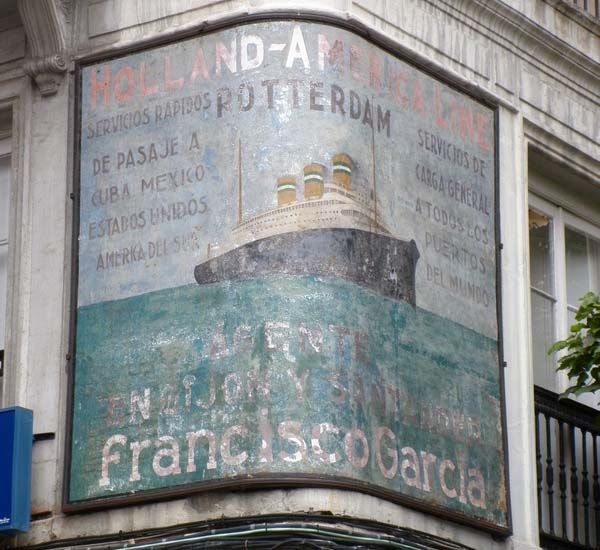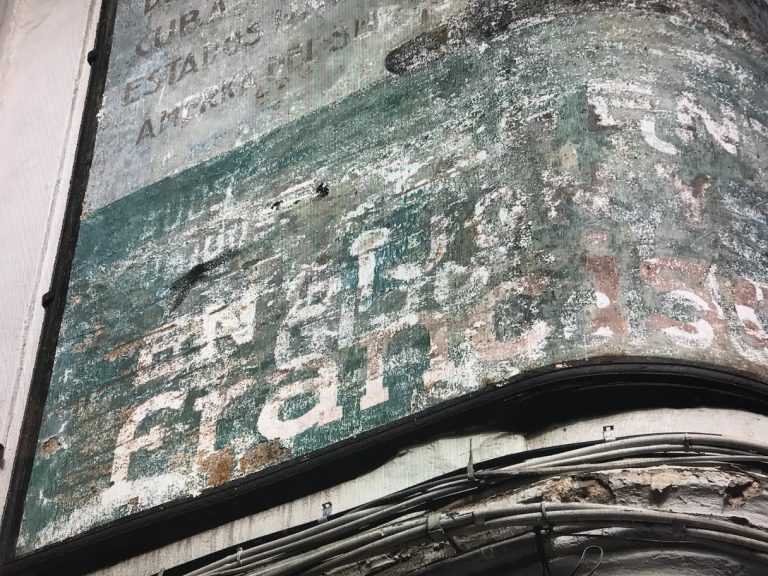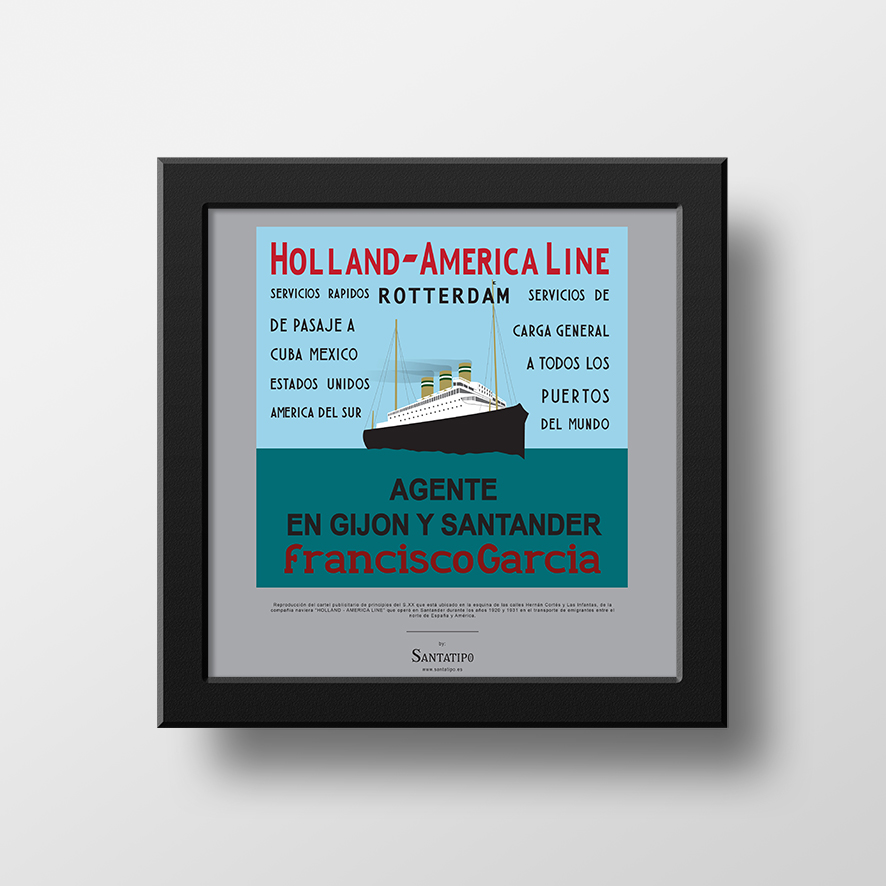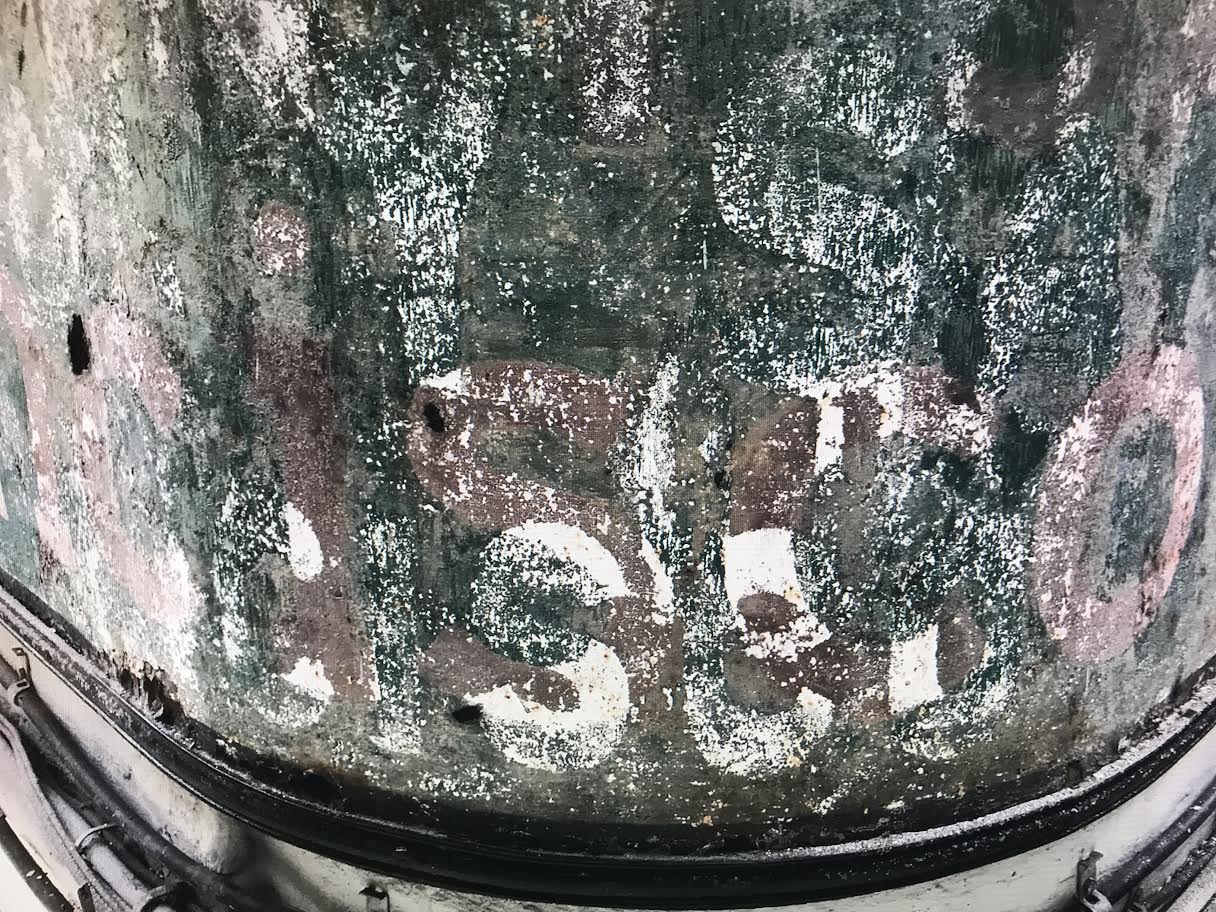
Cartel de Holland America – Line [Lámina descargable]
A veces la historia la tenemos a simple vista. Este es el caso. En la esquina de Hernán Cortés y Las Infantas (frente a Fotografía Zubieta) hay un cartel publicitario de la compañía holandesa HOLLAND – AMERICA LINE que ha permanecido impasible al paso del tiempo. Se puede datar en el primer tercio del siglo XX. Actualmente está bastante deteriorado y no luce con su mayor esplendor. Hace algunos años fue restaurado por la Escuela Taller de Santander, pero realmente necesita un tratamiento y una restauración especial, para que permanezca otros tantos años más.
Estado del cartel antes de la restauración  (Julio, 2016). Foto: Santatipo
Estado del cartel hoy, tras la restauración de 2017 (Foto: Santatipo, 2019)
Dicho esto, el trasfondo que nos cuenta ese cartel es que Santander fue puerto de emigrantes entre 1920 y 1931. Durante el periodo de entreguerras se produjo un importante flujo migratorio desde España hacia el continente americano. Los motivos son varios aunque el principal era el efecto llamada de nuevas oportunidades.
Holland America Line
El VOLENDAM atracado en Santander. Fuente «vida Marítima»
Es aquí cuando en 1920 la ya veterana por aquel entonces Holland America Lijn (1871) entra en el tráfico marítimo migratorio como línea regular desde el norte de España y Países Bajos, hacia Cuba, México y Estados Unidos. Era una flota de buques mixtos de carga y pasaje con los colores característicos de sus chimeneas que se ve en la ilustración y realizaba el itinerario desde Rotterdam con escalas en Amberes, Boulogne sur Mer, Bilbao, Santander, La Coruña, Vigo, La Habana, Veracruz, Tampico y Nueva Orleans, desde donde regresaba a Europa, con escalas en Veracruz, La Habana, Vigo, Santander y Rotterdam.
El SPAARNDAM atracado en Santander. Fuente "Vida Marítima"
El SPAARNDAM atracado en Santander. Fuente «Vida Marítima»
En la actualidad Holland – America Line continúa operando como una importante compañía de cruceros.
Esto es un breve resumen de lo que nos puede decir un simple cartel en una esquina, pero si quieres profundizar más sobre esto ya que apenas existe información y fuentes de la vinculación de la compañía «Holland – America Line» con Santander, te recomiendo leer el blog «Vida Marítima» de Arturo Paniagua Mazorra que ofrece una información exhaustiva sobre los barcos y líneas que fueron clave en los movimientos migratorios de principios del siglo XX, y de donde he podido rastrear y sacar la información que aquí cuento.
El nombre de Francisco García, aparte de que ser Historia Gráfica de la ciudad, hay que vincularlo a un famoso armardor en el norte de España que tuvo una gran flota (1). También su nombre está vinculado a otra empresa como es Freixenet. Su nieto Enrique Hevia García, proveniente de una familia con un negocio de licores en Peñacastillo, contrajo matrimonio en 1941 con Carmen Ferrer, una de las copropietarias de Freixenet, que vivió en el número 15 de Hernán Cortés hasta su fallecimiento en 2016. Otra curiosidad: Francisco García se hizo como casa de verano en 1916 la Finca Quinta de los Pinares, en el Sardinero, que fue vendida en los años 60 a la familia Santos (Hoteles Santos / Santemar).
Nueva restauración del cartel:
Fue en noviembre de 2017 llevada a cabo por GRAP, SL. Durante este último proceso de restauración, cabe destacar que aparecieron pruebas de diseño tipográfico, con distintas letras. Esto demuestra que el cartel se hizo in situ, dado que su ubicación en altura y forma esquina, obligaban a probar distitnos tamaños y propoporciones para su correcta lectura.
Desde Santatipo he querido homenajear a este fragmento de la Historia de Santander reproduciendo el cartel totalmente vectorizado con sus colores, a partir de la pigmentación existente y otros carteles similares de la época, así como esa tipografía que apenas se puede ver y leer.